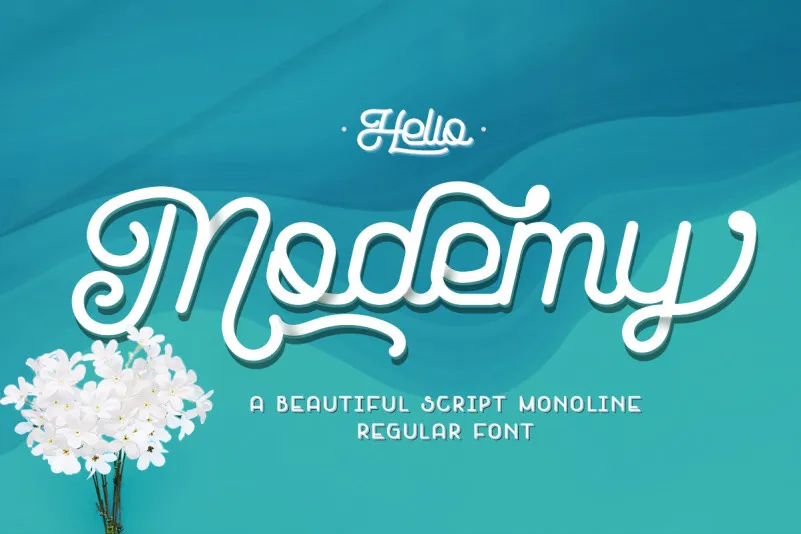
Esta é uma fonte de linhas monocônicas, criada para atender a diversos usos em design gráfico. Com duas estilos disponíveis, ela se adequa perfeitamente ao desenvolvimento de logomarcas, branding, desenho de roupas, sinalização, panfletagem e até mesmo convites de casamento. A intenção do designer mhdafifersya para essa fonte era criar um script monocóndico fácil de ler, adaptado para múltiplas finalidades. Modemy é uma font que transmite sensação de criação artesanal, com toques naturais antes de ser aperfeiçoada. Isso resulta em um conjunto consistente de caracteres que se adequam perfeitamente para seus projetos criativos. Suave e elegante, ela não só complementará sua identidade visual como também dará um toque autêntico aos seus materiais impressos.